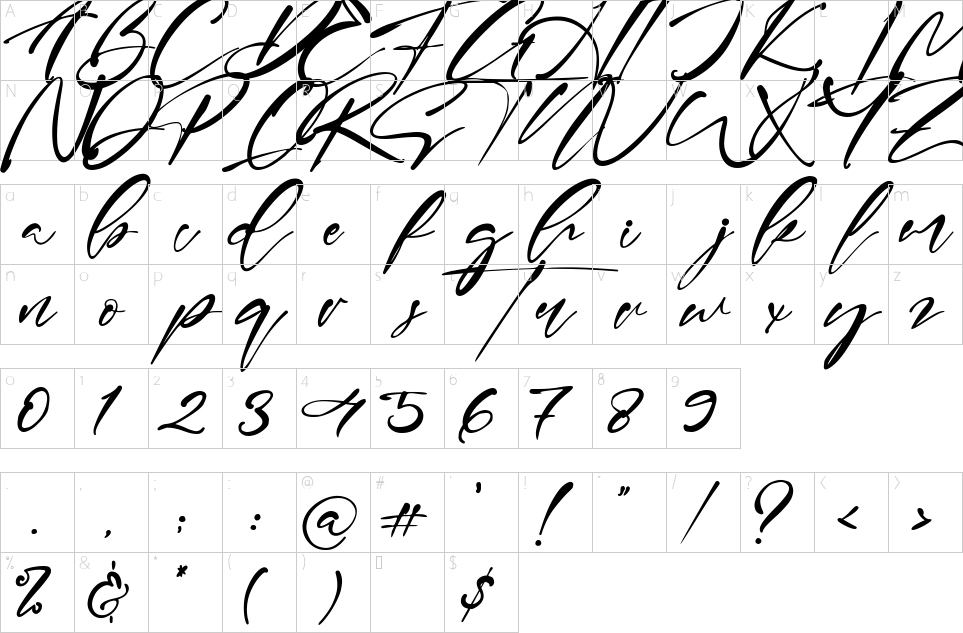
Angelina Rachmi Font – Fonte Grátis
Angelina Rachmi Font
Descubra a beleza de Angelina Rachmi, uma fonte elegante e suave que se destaca entre as outras. Desenvolvida pelo prodígio de StringLabs, Angelina Rachmi traz um toque de elegância e sofisticação. Seja para aplicativos de texto ou para criações digitais, essa fonte única é perfeita para quem valoriza uma fonte de alta qualidade. Disponível tanto para sistemas Windows quanto para Mac, você pode garantir um visual impecável em seus projetos. Com 730 downloads, Angelina Rachmi é uma escolha inteligente para qualquer designer gráfico que procura qualidade e personalidade para suas criações. Descubra agora mesmo Angelina Rachmi e transforme seu design.
Mapa de caracteres da fonte Angelina Rachmi Font